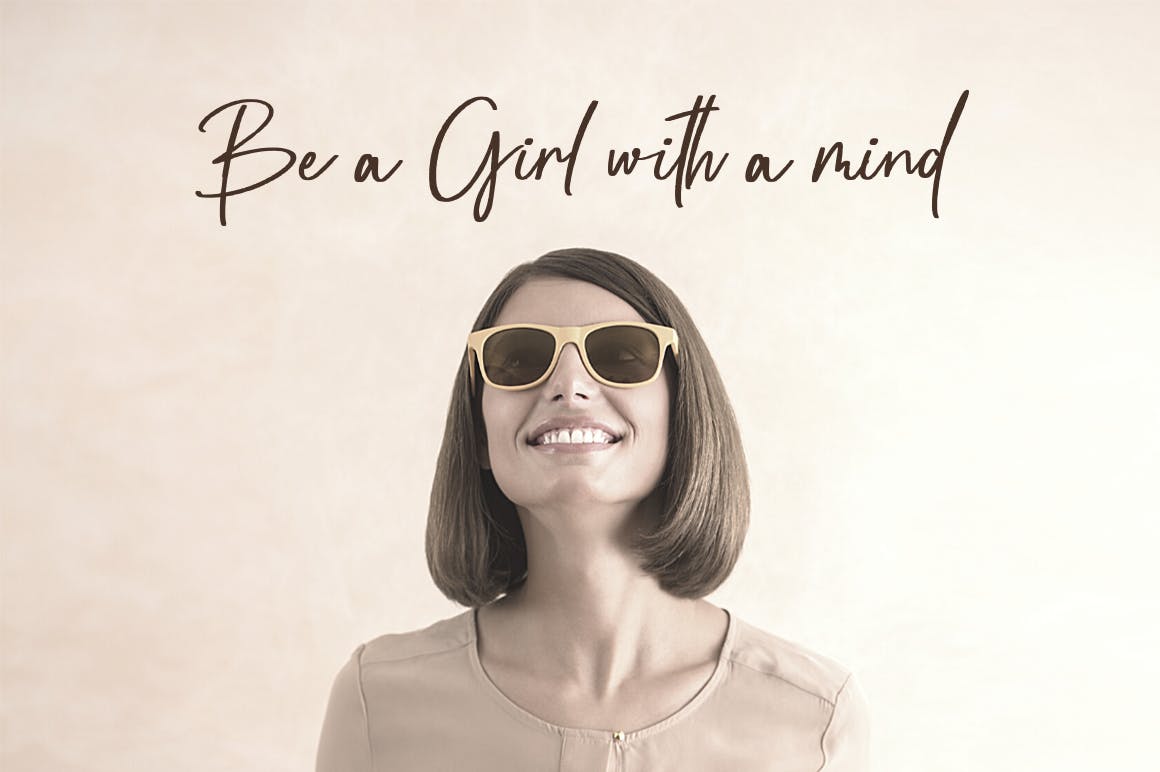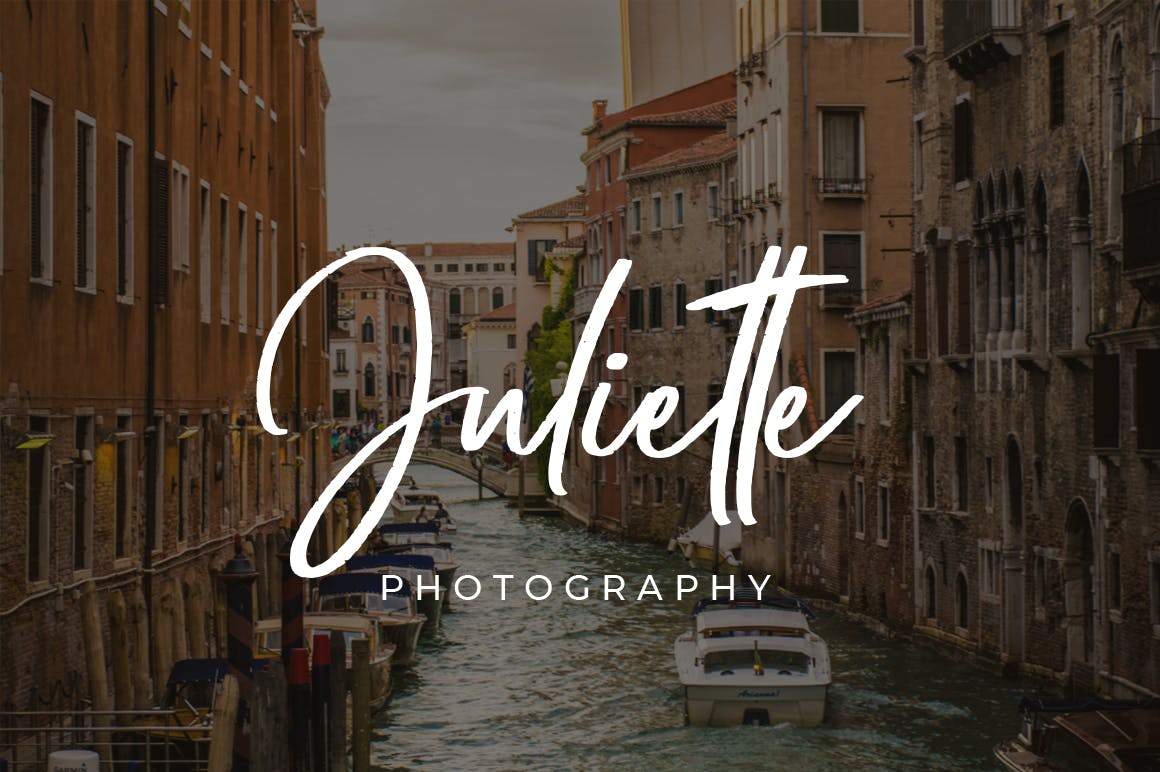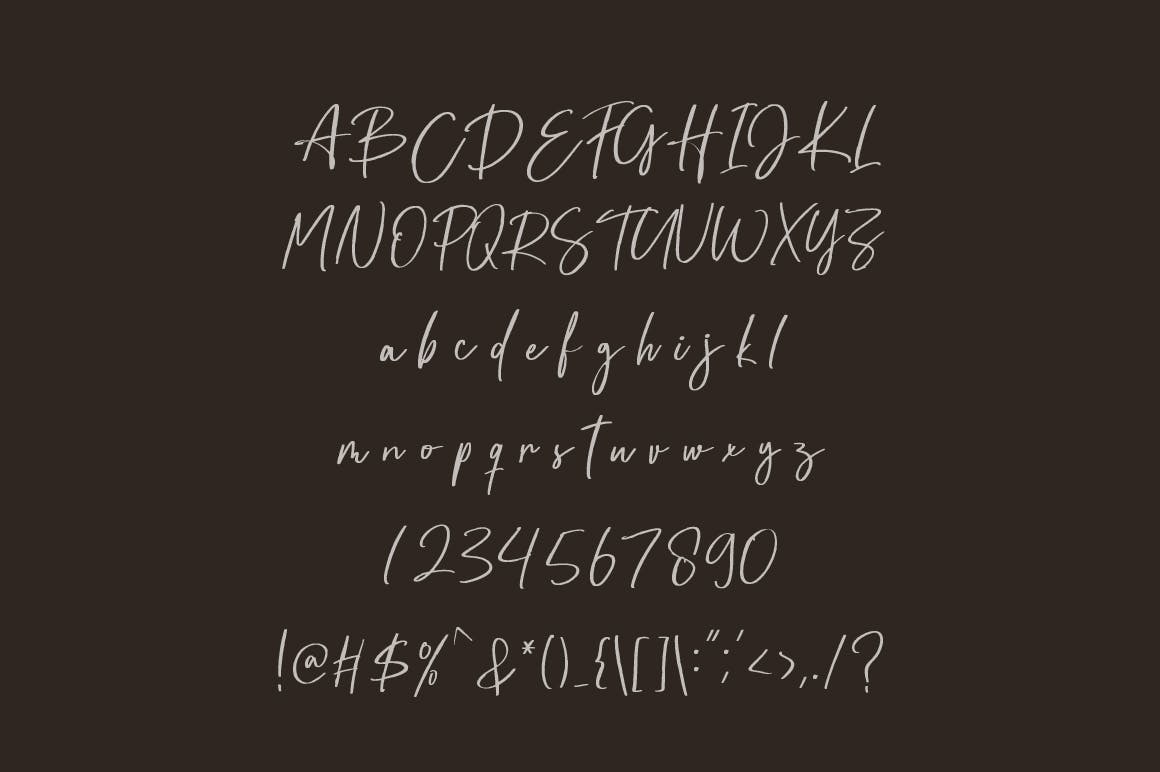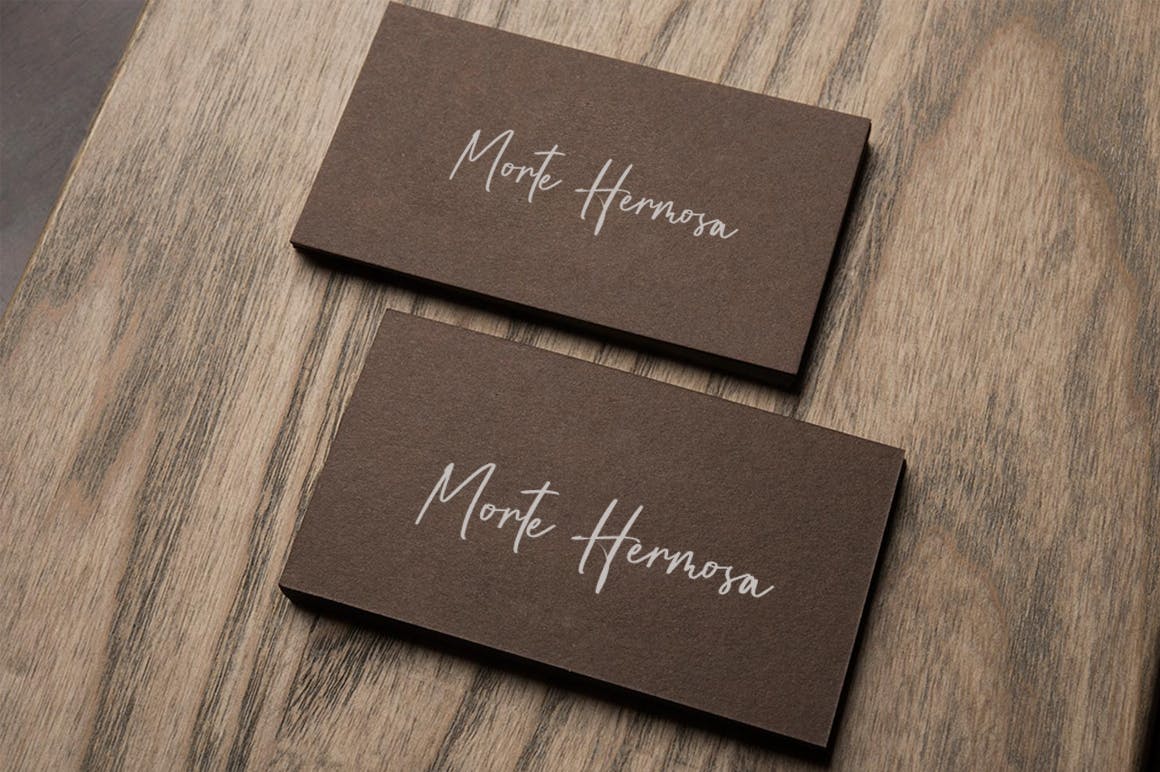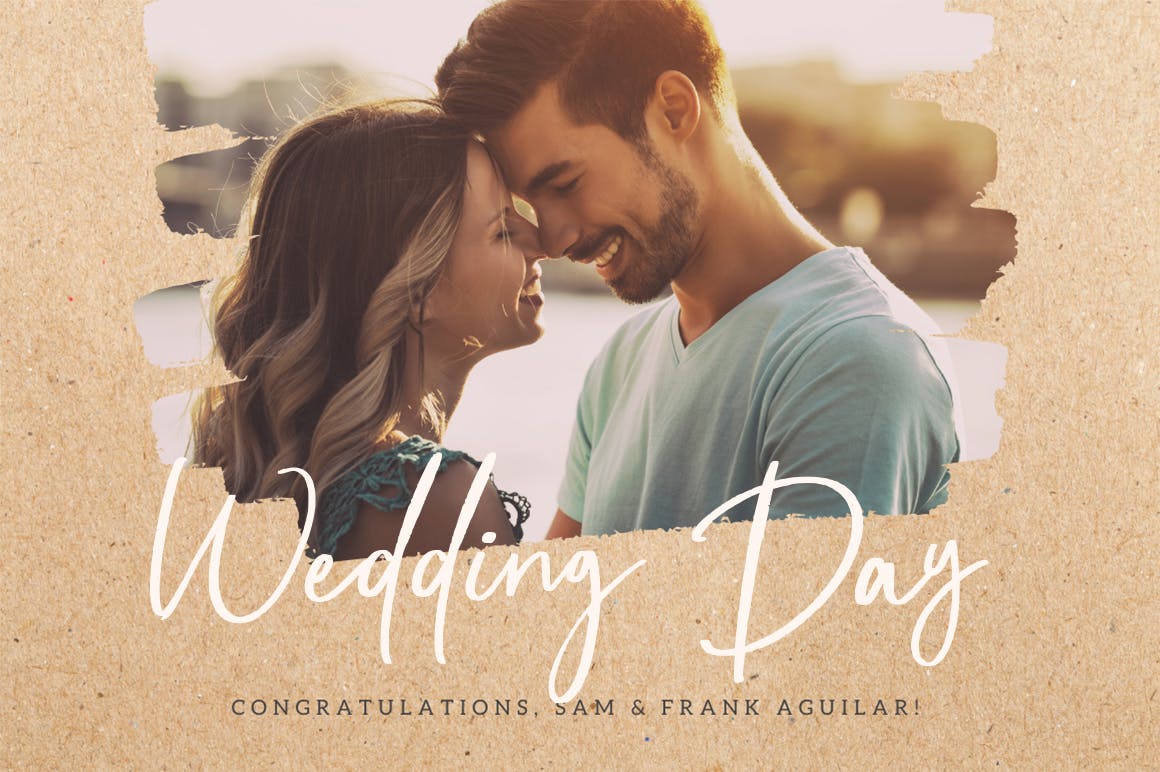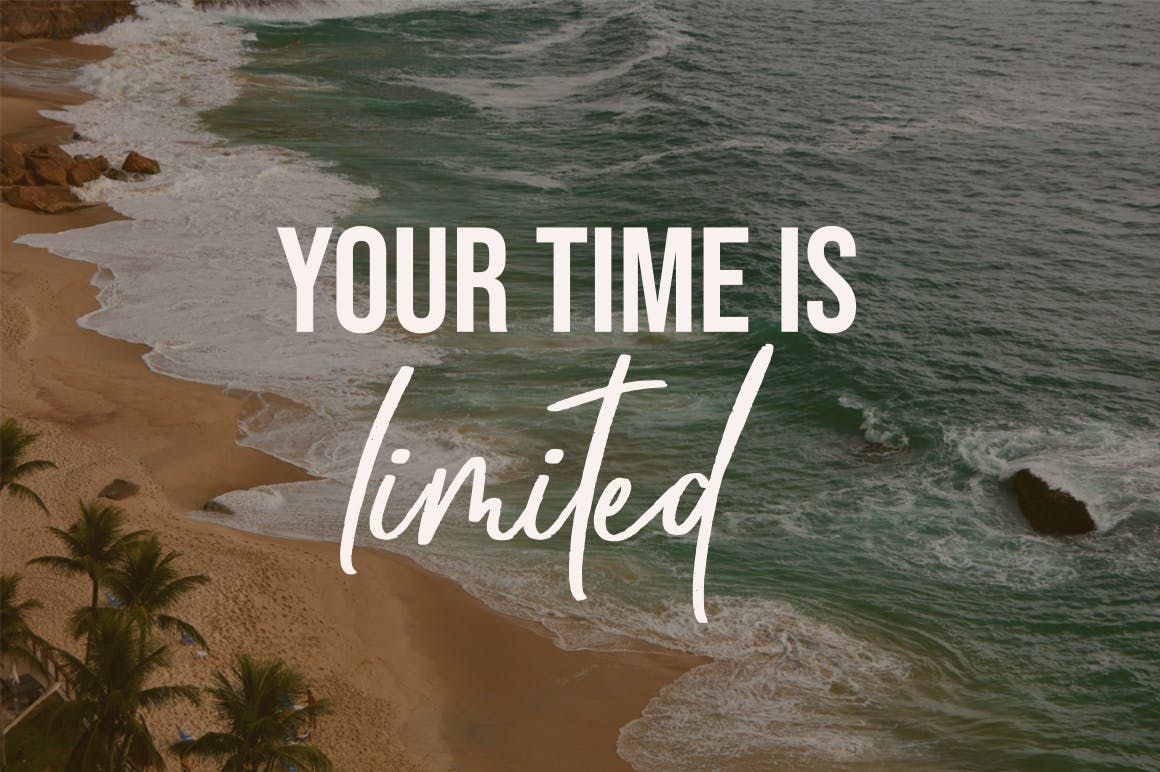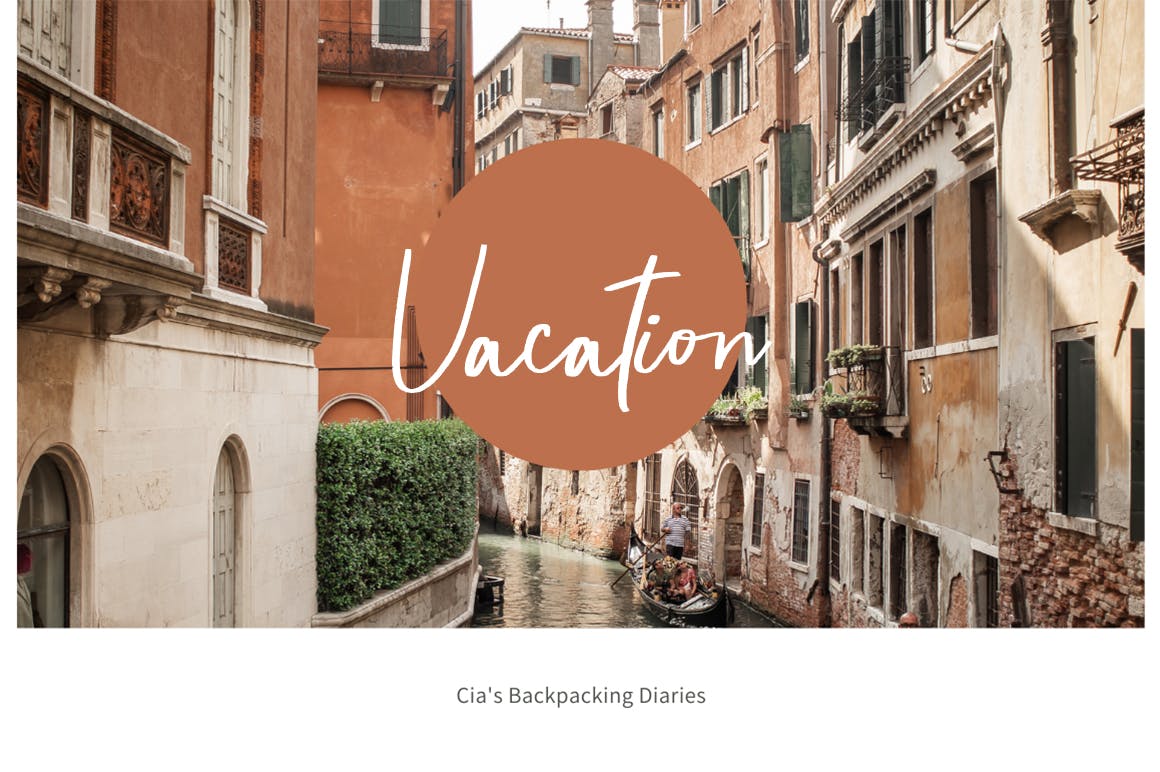
فونت هرسوند یک فونت دستنویس طبیعی است. شما یک مجموعه کامل از حروف کوچک و بزرگ، اعداد و علائم نگارشی، نمادهای چندزبانه، حروف کوچک جایگزین و بستهای از لیگاتورها را دریافت خواهید کرد. این فونت برای برندینگ، امضا، دعوتنامههای عروسی، تبلیغات، بستهبندی محصولات و سایر نیازها بسیار مناسب است. فونت هرسوند طبیعی، ساده، ولی در عین حال اصیل و بسیار شیک است.